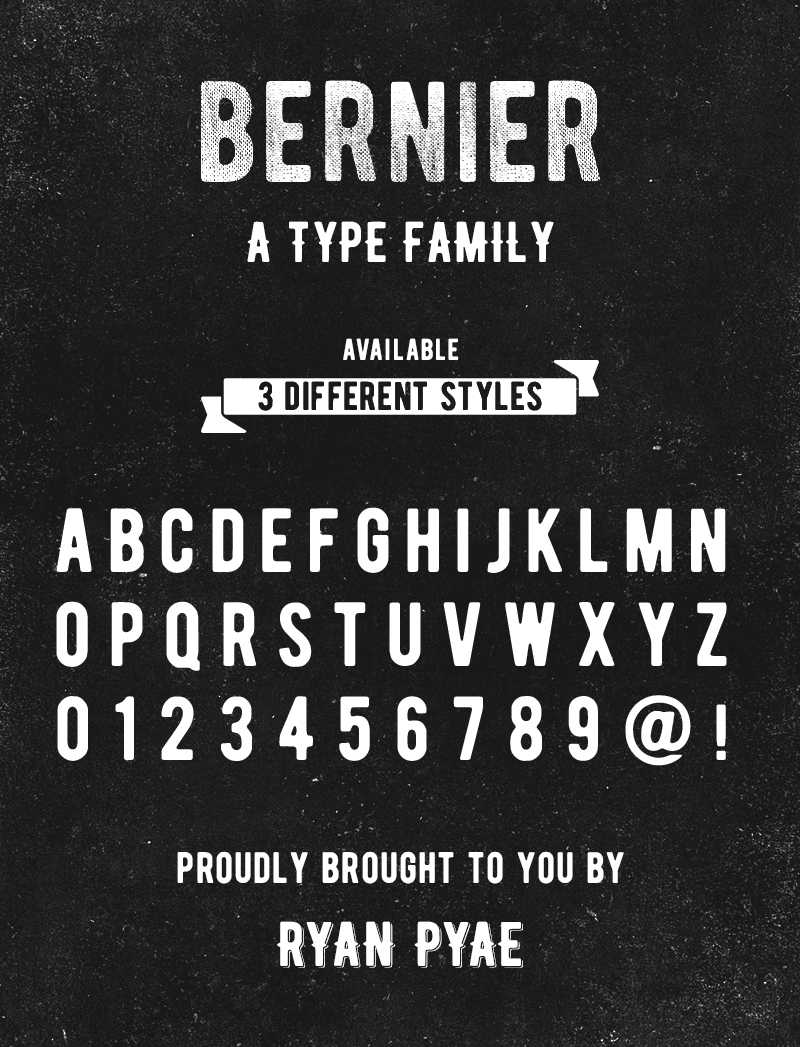
Bernier Display Font
Bernier Display é uma fonte que é perfeitamente adequada para qualquer tipo de design gráfico. Seja para adicionar um toque nostálgico em seus designers de identidade visual e selos vintage, ou para criar um logotipo único e moderno. A fonte Bernier Display oferece três formatos: regular, com sombreado e com desgaste, permitindo uma grande variedade de opções para personalizar seus projetos. Ela está disponível em todas as letras maiúsculas. Este recurso gráfico é ideal para designers que buscam uma fonte versátil e criativa para seus projetos, oferecendo um toque único que se encaixa perfeitamente em qualquer estilo de design.